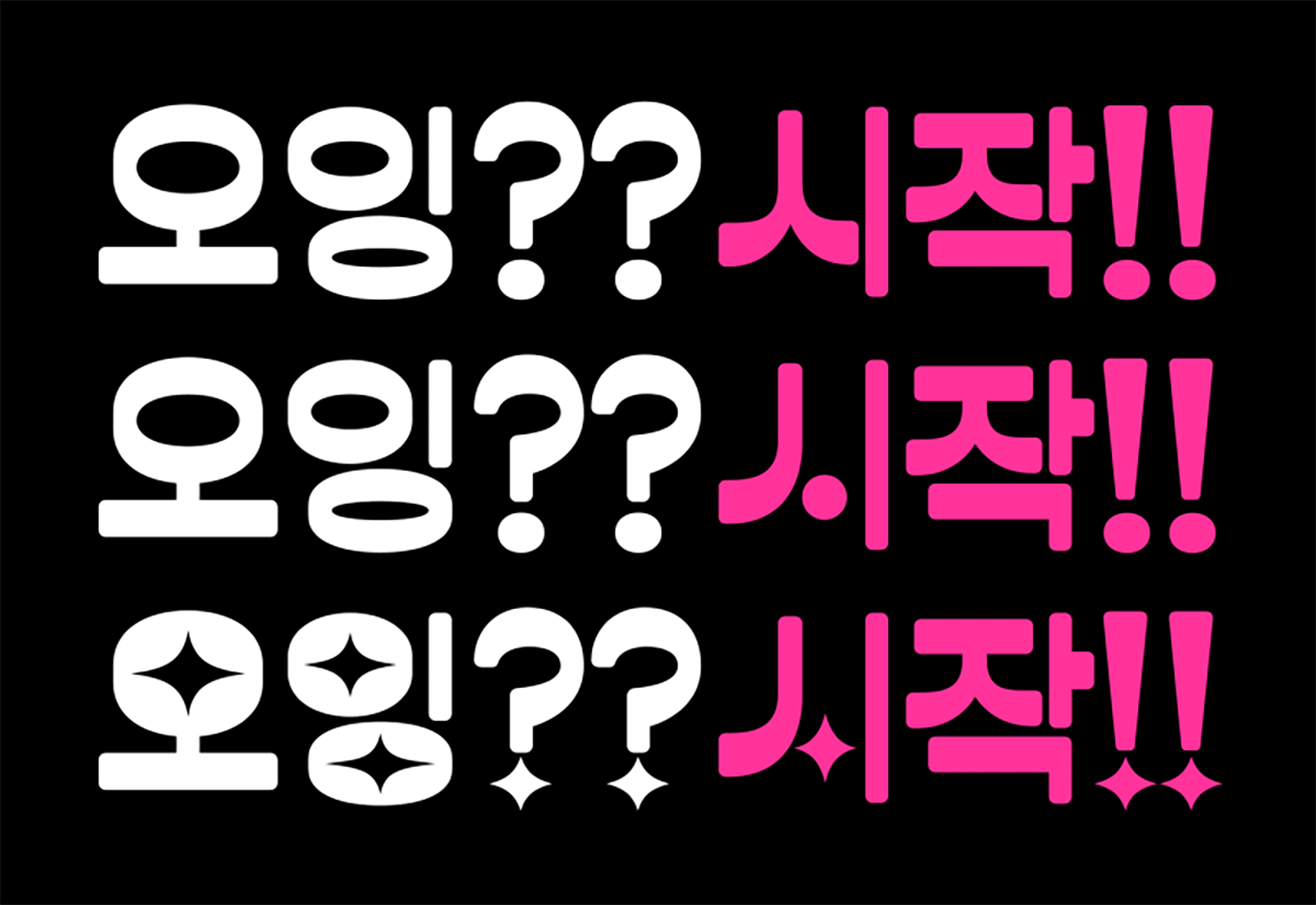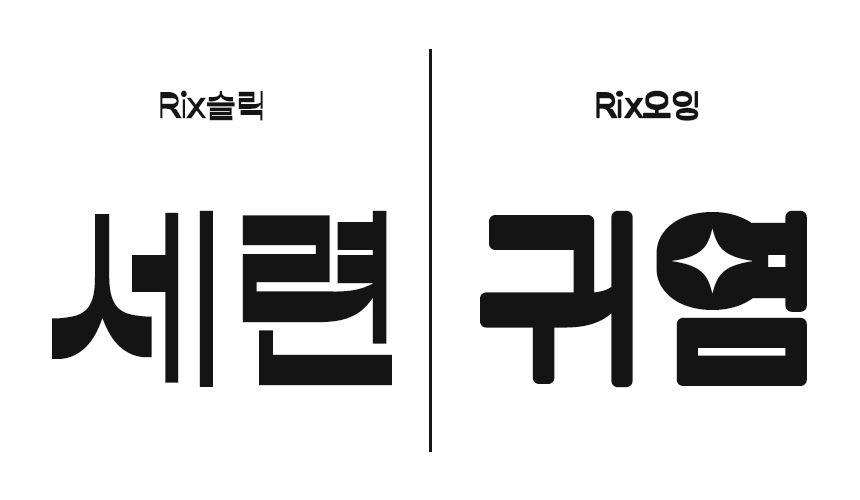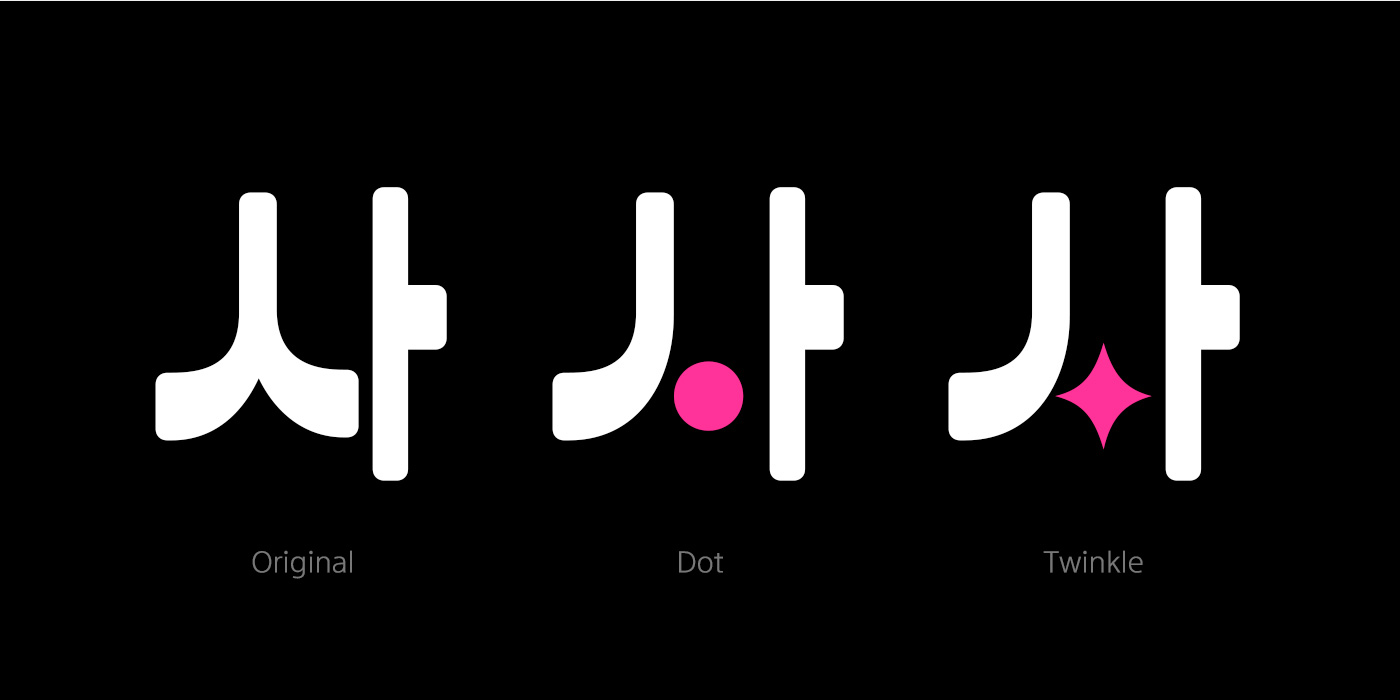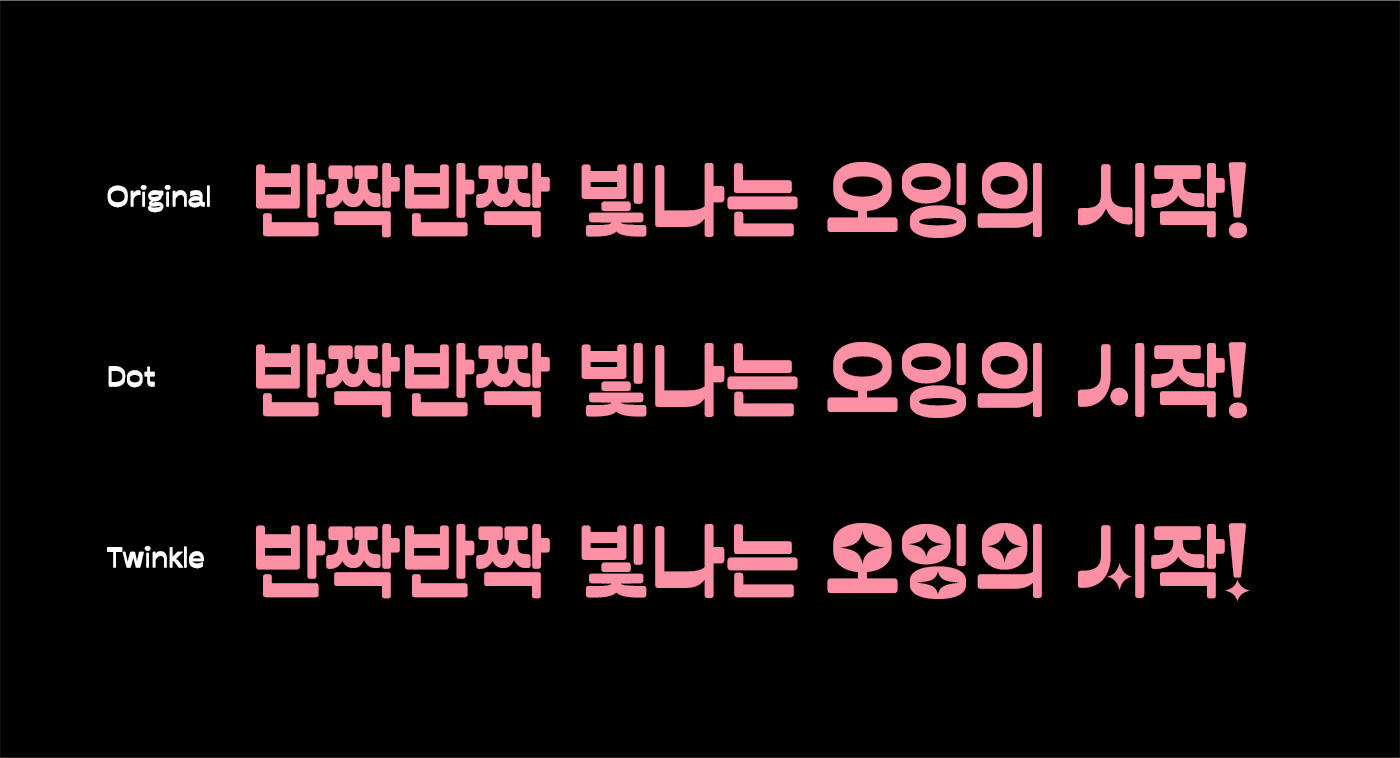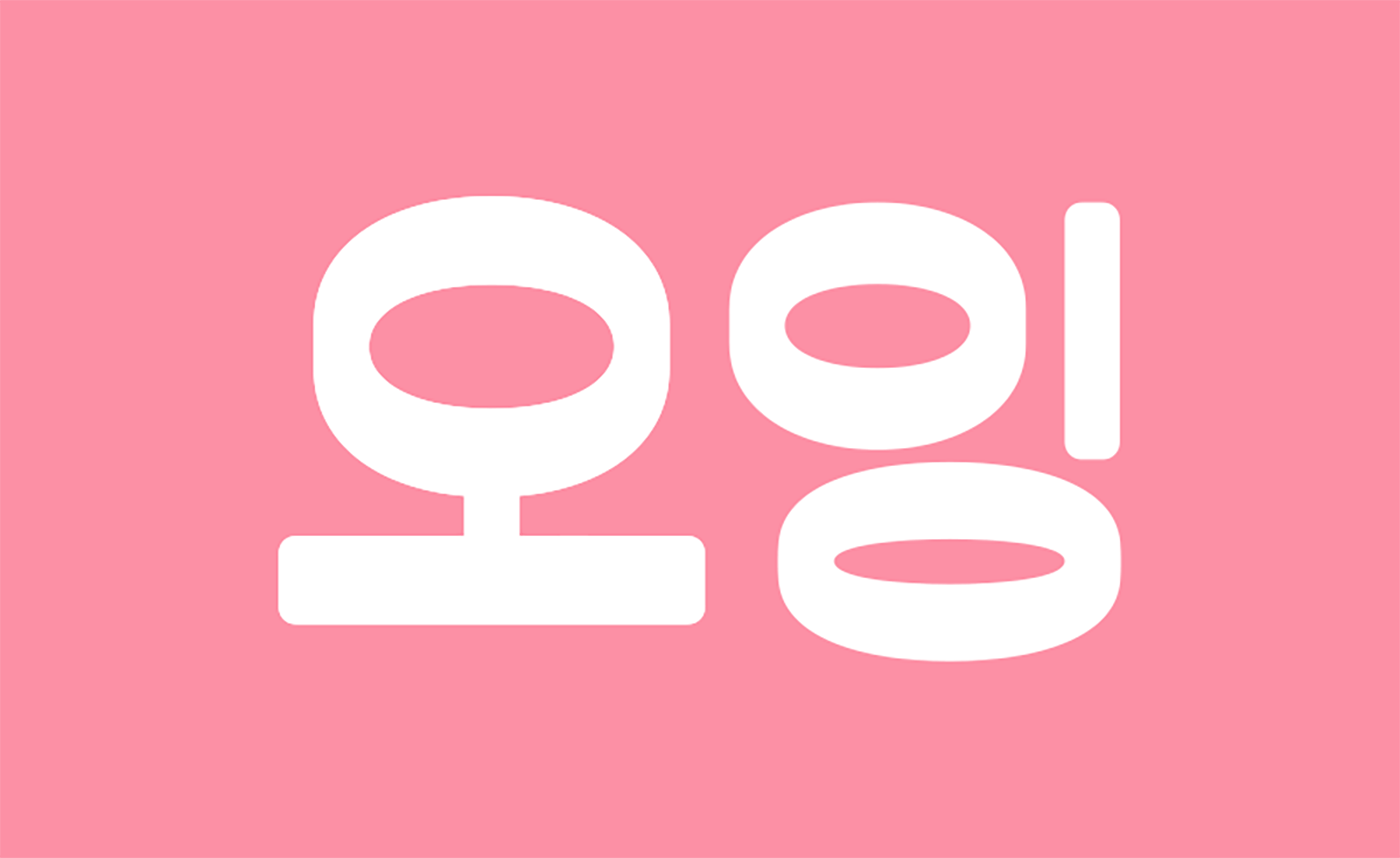
덥고 습해진 날씨로 왠지 몸도 마음도 다운되는 7월, 기분을 업 시켜줄 폰트를 소개합니다!✨ 7월의 신규 폰트는 부드러운 라운드 효과, 통통 튀는 세 가지 유니크한 디자인으로 중무장한 폰트 「Rix오잉」서체입니다. 폰트를 제작한 이수하 디자이너와의 인터뷰를 통해 더 자세히 알아보겠습니다 :)
안녕하세요. Rix힘을내요, Rix네모굴림 이후 'Rix오잉'으로 다시 돌아온 이수하입니다.
폰트명부터 재미있는 Rix오잉, 기획 배경이 궁금해요.
자사 폰트 중 Rix슬릭이 요즘 많이 보이는 가로 획이 굵고 세로 획이 얇은 특징을 가지고 있으며, 전체적으로 곡선과 직선의 조화가 세련된 폰트인데요. 그 반대인 ‘귀여운 버전도 있으면 어떨까?’라는 생각에서 시작되어 Rix슬릭 귀여운 버전으로 변형을 준 Rix오잉이 나오게 되었습니다!
제작자로서 가장 신경 쓴 부분?
가장 신경 쓴 부분은 Rix슬릭과 차별 점인 귀여운 느낌을 살리는 것이 중요해 여러 연구를 통해 많은 변화를 시도했는데요. 먼저 귀여운 느낌을 극대화하기 위해 초성 크기를 키우는 작업을 했습니다. 그 후 Rix오잉의 아이덴티티인 직선 구간이 있는 원형 형태를 더 잘 어울리도록 기존 정원 형태의 ‘ㅇ’ 꼴을 ‘ㅁ’ 꼴 디자인에 맞춰 골격을 변경했습니다. 마지막으로 전체적인 라운드 효과로 부드러운 인상을 극대화하는 작업을 마무리했습니다-!!
독특한 디자인 포인트들이 눈에 띄는데요, 각각의 디자인에 대한 설명을 좀 부탁드려요!
공통적인 디자인 포인트는 직선 구간 원형 형태가 주는 유니크함과 귀여운 느낌입니다. 그중 Dot은 ㅅ, ㅈ, ㅊ꼴 민글자에 빗침 대신 동그라미가 들어가 있으며, Twinkle은 ㅇ꼴 초·종성, ㅅ, ㅈ, ㅊ, ㅎ꼴 민글자에 반짝이는 디자인 포인트가 들어 간 차이점이 있습니다. 세 가지 다른 느낌으로 다양하게 서체를 사용하실 수 있으며, 영문 및 숫자, 약물에도 디자인에 맞춰 포인트들을 넣어 사용하실 때 찾는 재미가 있으실 것 같습니다 :)
Round 1. 스타일의 3단 변화
Rix오잉은 기본적으로 가로 획이 두껍고 세로 획이 비교적 얇은 획 대비를 갖고 있는 서체로 그래픽 폰트 Rix슬릭에서 변형을 준 서체입니다. 기존 Rix슬릭은 두께를 기준으로 2종으로 파생이 되었지만 Rix오잉은 두께감 있는 굵기로 통일되어 디자인을 기준으로 Original, Dot, Twinkle 총 세 가지 스타일로 제작되었습니다.
기본 서체인 Original, 일부 자소에 귀여운 동그란 포인트를 준 Dot, 독특한 속공간과 반짝이는 표현이 들어간 Twinkle까지 다양성을 갖춘 디자인들로 사용성을 높였습니다.
Round 2. 큼직하고 유니크 해!
Rix오잉은 전체적인 획 마무리를 라운드 효과로 처리하여 부드럽고 큼직한 초성의 크기가 귀여운 인상을 줍니다. 또한 전체적인 디자인에 어우러지도록 작업한 직선 구간이 있는 'ㅇ'꼴 자소는 독특한 형태감을 주어 Rix오잉만의 아이덴티티가 되었습니다.
전반적으로 둥글둥글하고 각각의 디자인마다 특징이 있어 다양하게 활용하기 좋습니다. 영문, 숫자, 일부 특문 등에도 같은 특징들이 적용되어 있어 찾는 재미도 있고 조화롭게 사용 가능해요!
Round 3. Rix오잉 찰떡 활용법
귀엽고 통통 튀는 이미지와 잘 어우러지는 Rix오잉 폰트는 각종 포스터나 패키지 타이틀 등에 활용하기 좋은 디자인 서체입니다. 폰트 자체의 디자인만으로도 눈길을 끄는 상품을 만들 수 있어요.
오늘은 반짝반짝 독특하고 귀여운 서체 Rix오잉 폰트를 소개해 드렸습니다. 아무래도 포인트가 되는 디자인과 다부진 두께로 타이틀에 많이 활용될 것 같은데요~ 써볼수록 매력이 많은 폰트라 앞으로의 활약이 기대가 됩니다. 다양한 콘텐츠에서 만날 수 있길!